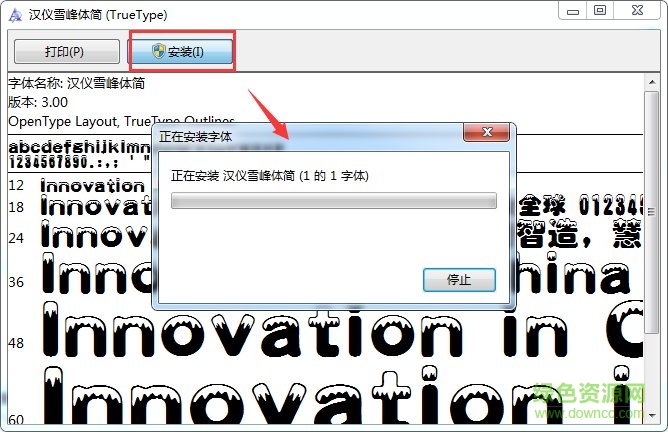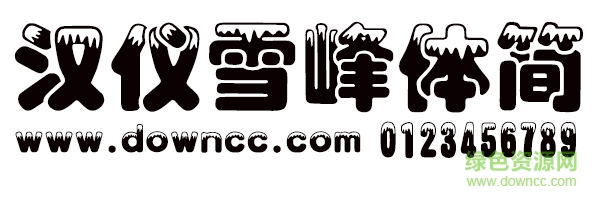
漢儀雪峰體簡ttf是一個(gè)非常美觀的字體資源。小編還是比較喜歡這款字體風(fēng)格的,輸出的文字很有靈性,常被用來設(shè)計(jì)一些平面設(shè)計(jì)和畫冊等。趕快來綠色資源網(wǎng)下載吧。
漢儀雪峰體簡字體今天分享給大家,第一感覺想到什么?我想到的是雪糕,清爽的感覺,你喜歡嗎?本作品可用于廣告設(shè)計(jì)字體、網(wǎng)頁設(shè)計(jì)字體、包裝設(shè)計(jì)字體、屏幕顯示字體等!